现代的尤其是年轻人很多都喜欢在身上纹纹身,那么我们都知道纹身是非常有个性而且很美观的。而且纹身有很多的形式,有图画的也有汉字的,还有英文字母的。看一下纹身英文字体有什么特点。
那么纹身英文字体第一个特点就是样式多,因为英文是由26个字母组成的,每个字母都可以进行一定的设计。而且有各种各样形式的字母,有大写小写的。样式的话你可以选择中规中矩的,也可以选择套路之外的,反正没有你找不到的只有你想不到的。这一点比起中文来说纹身英文字体的样式更多。而且有的人本身就喜欢夸张一点的,所以肯定是样式越多越好看了。
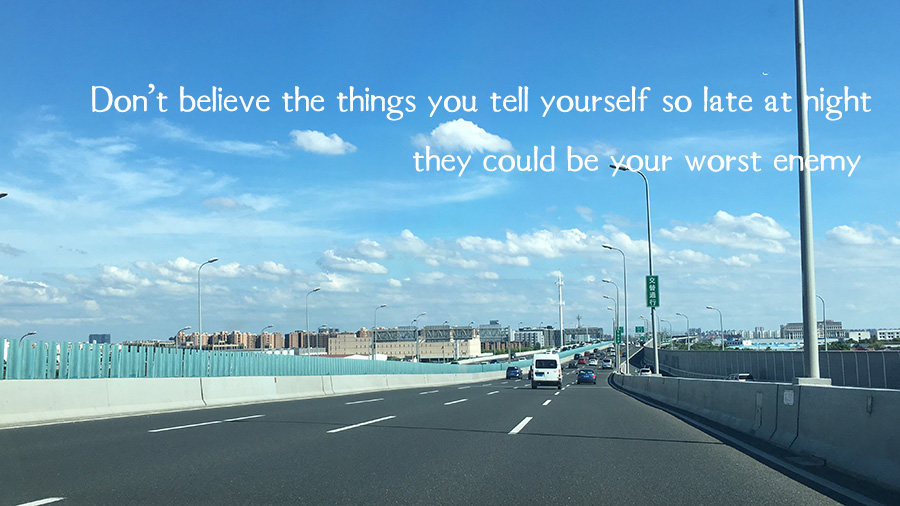
男女都适用也是因为纹身英文字体的样式多,所以有符合男生女生的字体。符合男生选择的字体就是比较粗犷或者比较夸张的;符合女生喜欢的就比较小一点,比较秀气的。
最后这个特点就是纹身英文字体设计,一个单词的设计可以由任何一个字母不一样而导致这个单词的效果不一样,所以你可以随意选择。每个英文字母之间你可以选择用弯曲的曲线连接,看起来就比较的潇洒;你也可以选择不连接,就显得特别的干净和简约。所以不同的设计法表现出的样式差别很大,这个大家可以自己根据自己的需要去选择。